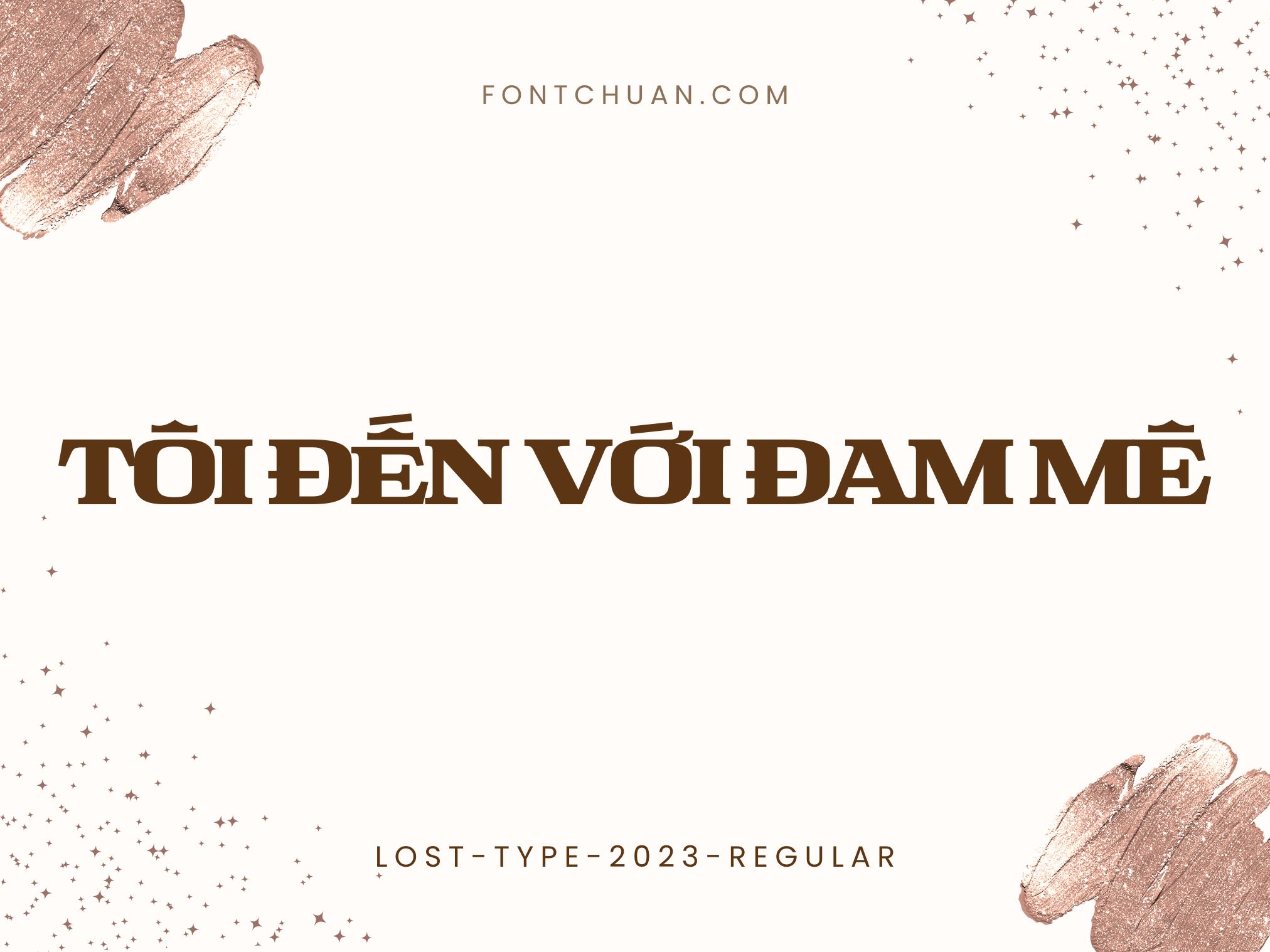
Lost Type 2023, hay còn được gọi là Lạc Tự, là một phông chữ serif cổ điển được thiết kế bởi Mack Trinh và Harry Dinh. Phiên bản mới nhất của phông chữ này ra mắt vào năm 2023, mang đến chất lượng hoàn thiện tốt hơn so với phiên bản đầu tiên ra mắt năm 2016. Lấy cảm hứng từ di sản typographic phong phú của Việt Nam, đặc biệt là các bảng hiệu cửa hàng, áp phích và quảng cáo từ những năm 1980 và 1990, Lost Type 2023 tái hiện lại tinh thần của thời đại đã qua, nơi những mẫu chữ in đậm trang trí mặt tiền cửa hàng, để lại dấu ấn không thể xóa nhòa trên cảnh quan đô thị. Phông chữ này đã được Việt hóa bởi chính các tác giả, Mack Trinh và Harry Dinh, nhằm hỗ trợ đầy đủ các ký tự tiếng Việt, mang lại trải nghiệm gõ chữ trọn vẹn cho người dùng Việt Nam. Ngoài tiếng Việt, Lost Type 2023 còn hỗ trợ nhiều ngôn ngữ khác, mở rộng khả năng ứng dụng trong các dự án quốc tế. Việc Việt hóa này được thành viên của Font Chuẩn chọn lọc và sưu tầm, nhằm đáp ứng nhu cầu bạn đọc và ứng dụng thực tế vào các dự án thiết kế.
Về đặc điểm thiết kế, Lost Type 2023 thuộc loại Font Display với cấu trúc hình hộp và rộng hơn, nâng cao tác động thị giác và khả năng đọc. Tính chất viết hoa toàn bộ của phông chữ này còn làm tăng sự hiện diện mạnh mẽ, biến nó thành lựa chọn lý tưởng cho tiêu đề, biển hiệu, logo và các ấn phẩm thương hiệu lấy cảm hứng cổ điển. Đồng thời, Lost Type 2023 cũng là một Font chữ Công nghệ, rất phù hợp cho các thiết kế mang tính hiện đại, sáng tạo, áp phích quảng cáo, bao bì sản phẩm và các dự án truyền thông số, giúp tạo điểm nhấn mạnh mẽ trong các lĩnh vực liên quan đến công nghệ và truyền thông số.
Phông chữ này đã được Việt hóa bởi chính các tác giả, Mack Trinh và Harry Dinh, nhằm hỗ trợ đầy đủ các ký tự tiếng Việt, mang lại trải nghiệm gõ chữ trọn vẹn cho người dùng Việt Nam. Ngoài tiếng Việt, Lost Type 2023 còn hỗ trợ nhiều ngôn ngữ khác, mở rộng khả năng ứng dụng trong các dự án quốc tế. Việc Việt hóa này được thành viên của Font Chuẩn chọn lọc và sưu tầm, nhằm đáp ứng nhu cầu bạn đọc và ứng dụng thực tế vào các dự án thiết kế. Với sự đầu tư chỉnh chu này, Lost Type 2023 được đánh giá cao và nó cũng là một dạng Font chữ Halloween vốn nổi tiếng về tính sáng tạo và khả năng truyền tải cảm xúc mạnh mẽ.